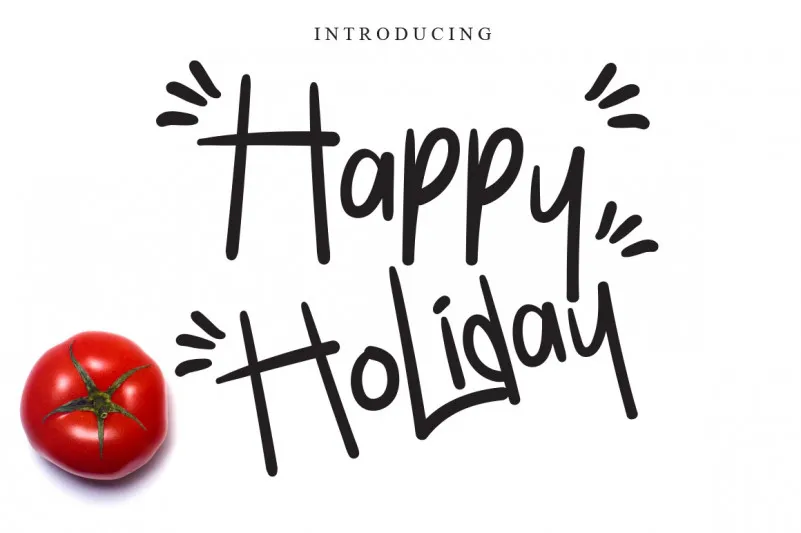
Happy Holiday Font – Download Grátis
A fonte “Happy Holiday Font” é uma seleção elegante e única de letras escritas a mão que se destaca nas categorias de design personalizado, especialmente para festivais de fim de ano. Seu estilo gráfico sofisticado é perfeito para um vasto conjunto de projetos, como cartões de agradecimento, convites de casamento, cartazes de aniversário e logomarcas. Suavemente charmosa, essa fonte será o toque final que tornará seus designs singulares ainda mais únicos. Seja você um designer especializado ou apenas uma pessoa com interesses criativos, a font “Happy Holiday Font” oferece o toque perfeito de personalidade e estilo para qualquer projeto de design gráfico que precisa de uma pegada única e encantadora.